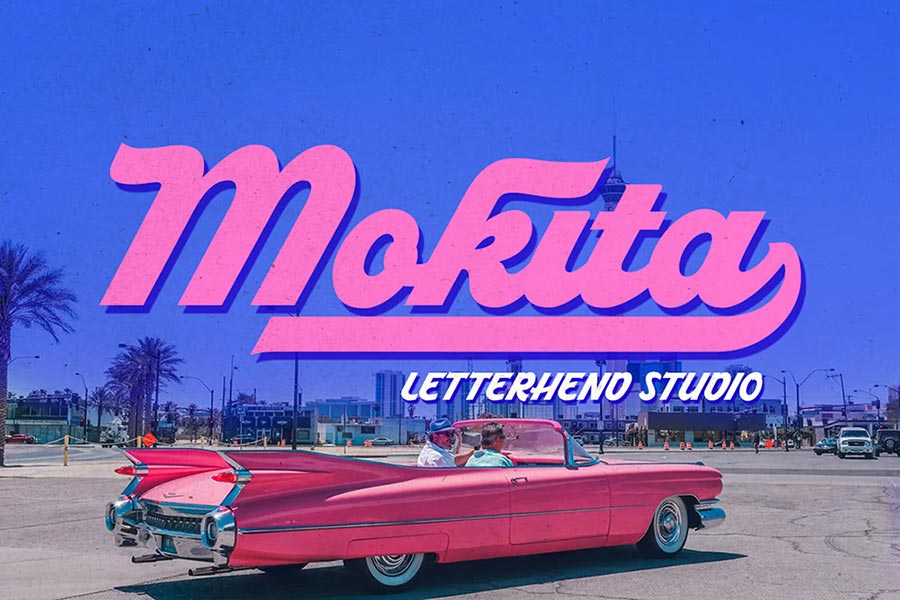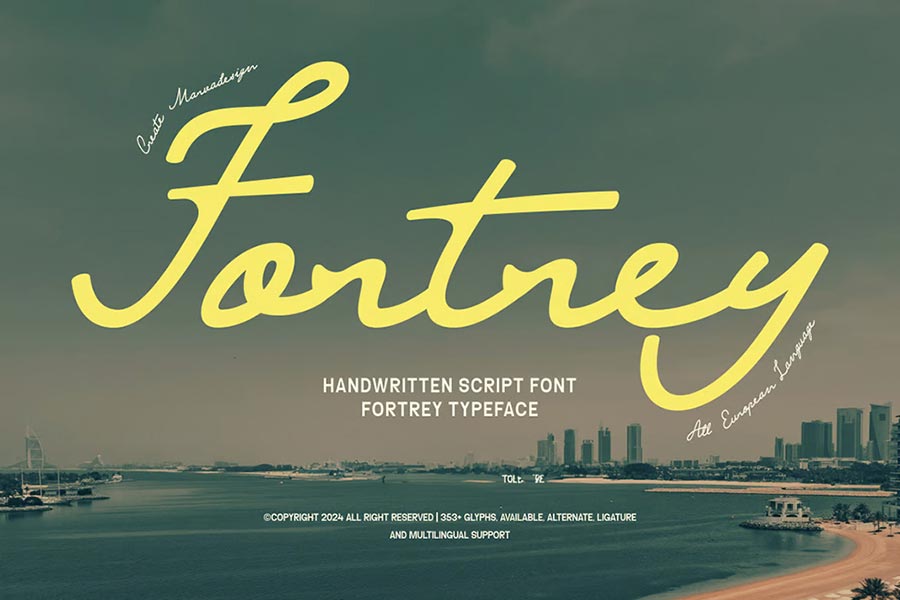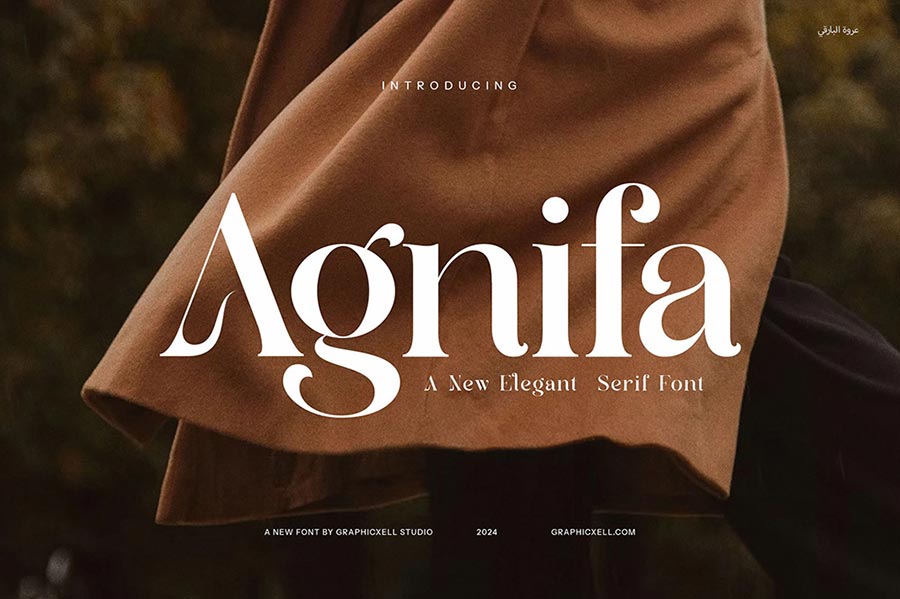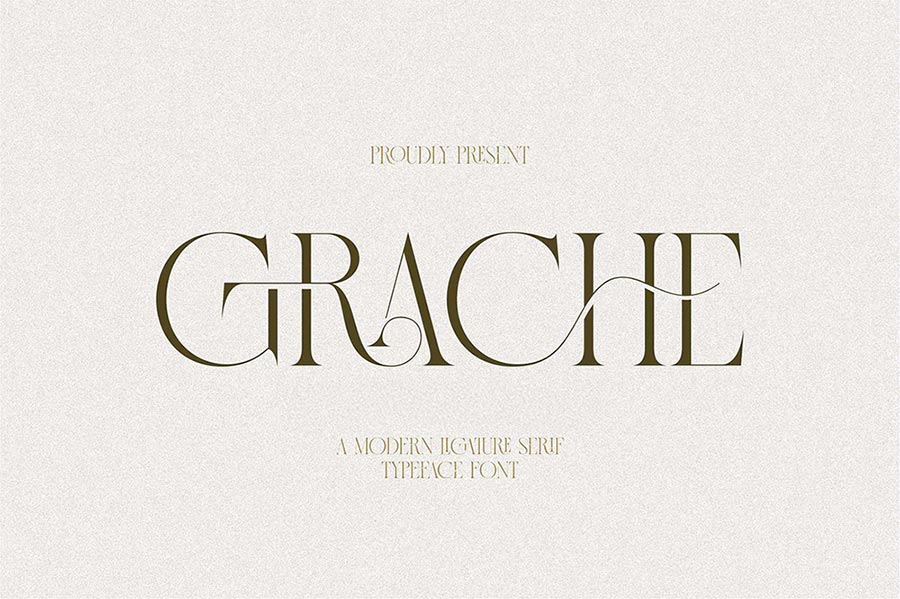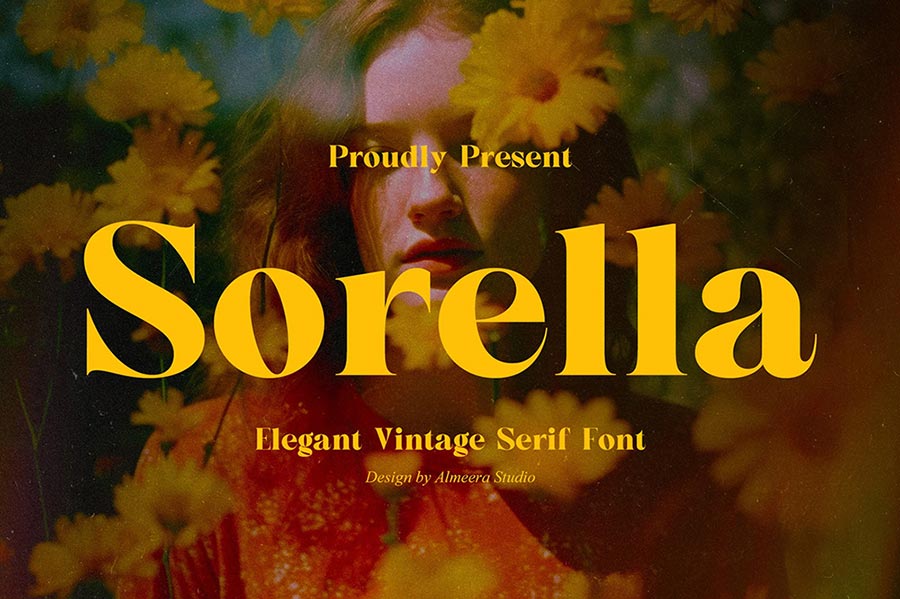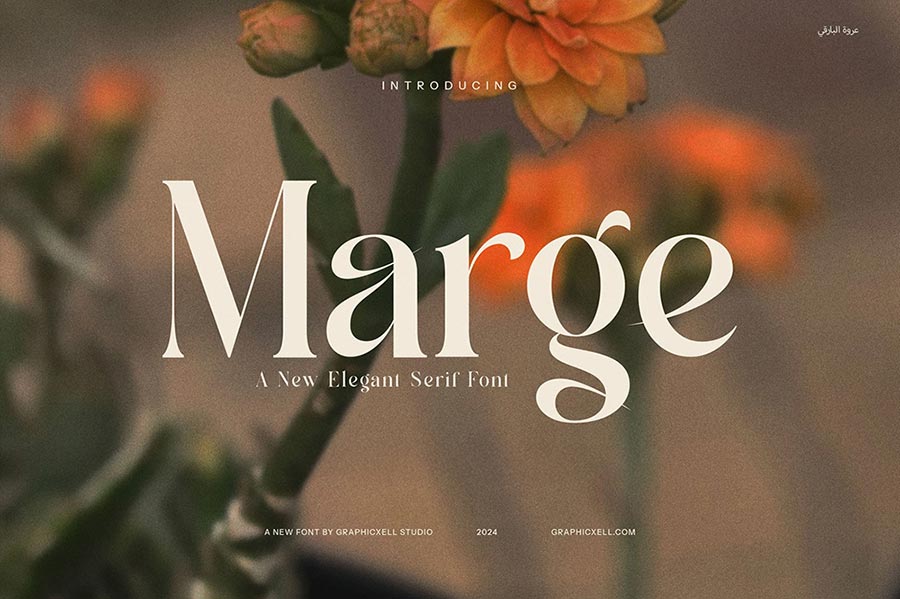
Chia Sẻ Miễn Phí 5+ Font Chữ Siêu Đẹp Siêu Mới Ấn Tượng
Trong lĩnh vực thiết kế đồ họa, font chữ đóng vai trò vô cùng quan trọng trong việc truyền tải thông điệp và tạo nên sự độc đáo cho mỗi dự án. Hiểu được nhu cầu đó, Sadesign.vn đã tổng hợp và chia sẻ miễn phí hơn 5 font chữ siêu đẹp, siêu mới và đầy ấn tượng, giúp các nhà thiết kế có thêm nguồn tài nguyên phong phú để sáng tạo.
1. Font chữ tối giản nhưng hiện đại
Font chữ này mang phong cách tối giản, phù hợp với các thiết kế hiện đại hoặc tối ưu cho các thương hiệu muốn nhấn mạnh sự tinh tế. Với các đường nét sắc sảo và cân đối, đây là lựa chọn lý tưởng cho logo, tiêu đề hoặc các ấn phẩm quảng cáo.
2. Font chữ viết tay mềm mại
Nếu bạn đang tìm kiếm một font chữ mang cảm giác gần gũi và tự nhiên, thì font chữ viết tay sẽ là sự lựa chọn hoàn hảo. Loại font này thường được sử dụng trong các thiết kế thiệp mời, poster nghệ thuật hoặc các dự án mang tính cá nhân hóa cao.
3. Font chữ cổ điển đầy sang trọng
Phong cách cổ điển chưa bao giờ lỗi thời trong thiết kế. Font chữ cổ điển mà Sadesign.vn chia sẻ mang lại cảm giác sang trọng, quý phái, phù hợp với các dự án về thời trang, nhà hàng cao cấp hoặc các thương hiệu lâu đời.
4. Font chữ sáng tạo độc đáo
Đối với những nhà thiết kế muốn tạo sự khác biệt, font chữ sáng tạo với các đường nét phá cách sẽ là điểm nhấn đáng giá. Loại font này thường được sử dụng trong các dự án nghệ thuật, thiết kế bìa sách hoặc giao diện kỹ thuật số.
5. Font chữ kiểu dáng công nghệ
Trong thời đại kỹ thuật số, các font chữ mang hơi hướng công nghệ cao luôn được yêu thích. Font chữ này thường có thiết kế góc cạnh và hiện đại, phù hợp với các dự án liên quan đến công nghệ, khoa học hoặc startup.
6. Font chữ đa năng cho mọi dự án
Đây là loại font chữ có tính ứng dụng cao, dễ dàng kết hợp với nhiều phong cách thiết kế khác nhau. Với sự linh hoạt này, bạn có thể sử dụng nó cho nhiều mục đích như in ấn, thiết kế website hay truyền thông mạng xã hội.